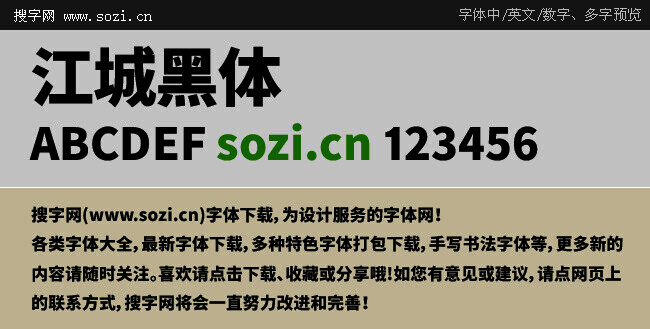
江城黑體
搜字網(wǎng)給大家提供一款江城黑體中文字體下載,江城黑體是一款基于思源黑體改造的中文字體,該字體簡(jiǎn)潔大方,個(gè)性醒目,具有強(qiáng)烈的視覺(jué)沖擊力。字體適合標(biāo)題設(shè)計(jì)、海報(bào)設(shè)計(jì)、包裝設(shè)計(jì)等應(yīng)用。